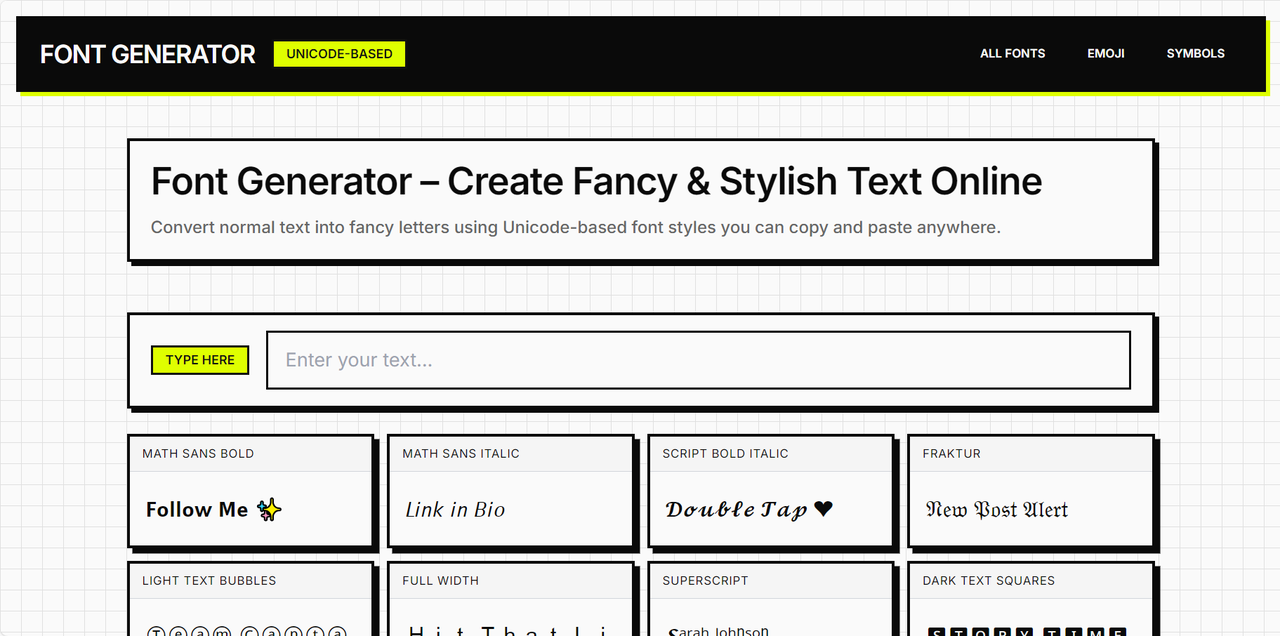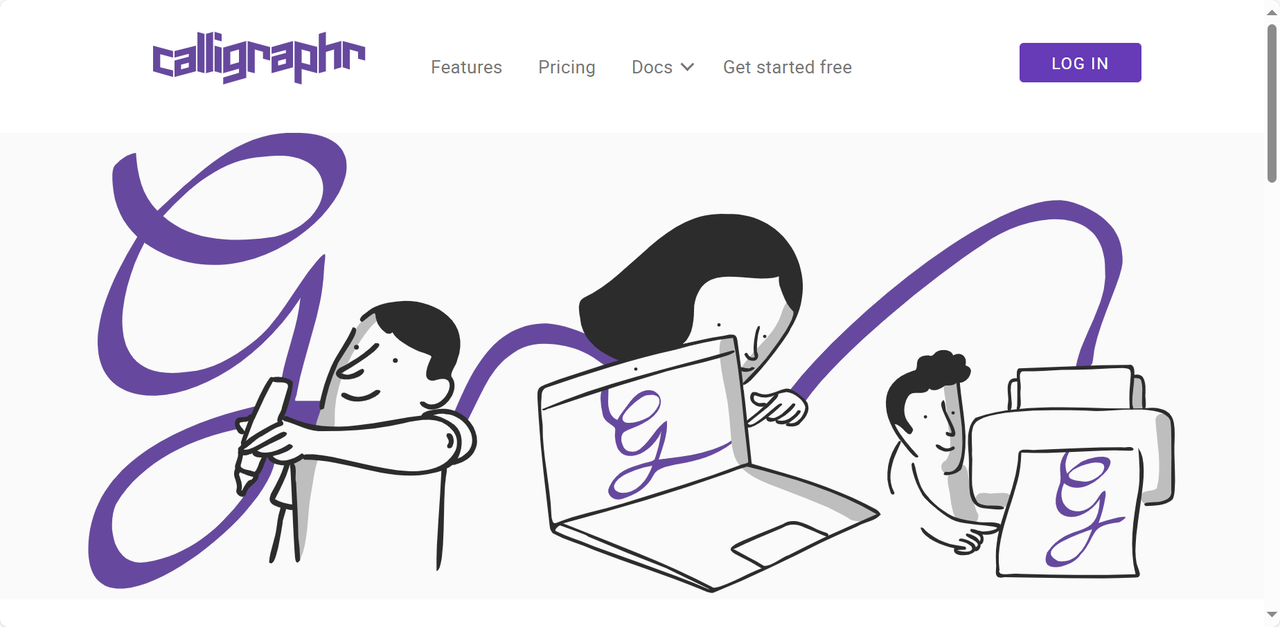
不用安装软件!在线实现字体转换,多重风格任你挑
经常做设计的小伙伴们都知道字体的重要性,往往系统自带的字体库是不够用的,普通字体也难以达到我们想要的效果,全网搜刮字体还总会遇到各种广告。今天给大家整理了 6 款不用安装软件就能使用的字体转换器,打开网页就能用,多重风格任你挑选。即使是新手小白也能快速进行字体转换,得到自己满意的字体效果!这些字体转换器的操作逻辑各不相同,擅长的字体风格也不太一样,接下来会给大家详细介绍每个工具的特色功能,帮助你选择最适合的自己的那一款。
一、字由
字由是一个集字体资源、字体管理和 AI 工具于一体的综合性工具,目前注册用户远超 2000 万,累计收录了上万款字体资源,明确标注可以免费商用的字体也有 3580+ 款,几乎适配所有日常需求。
关于字体转化,字由也为大家提供了多种方式:
- 第一种:实现多种风格的字体转化
进入字由官网之后,点击【全部字体】,这里有超多不同类型的字体资源,按照风格或字体类型可以进行筛选。选中你心仪的字体,在字体详情页面输出文字,就能一键转化为当前的字体效果,非常方便。最值得一提的就是,这些字体资源都清晰标注了授权类型,保证让大家放心使用,免遭版权问题的困扰。
- 第二种:实现艺术字的转化
同样也是进入字由官网,在顶部导航栏找到【字体工具】-【 AI 字体】,这也是字由的特色功能之一。这里有丰富多彩的艺术字模板,比如霓虹效果、书法水墨风、涂鸦风、文艺手写风等等,每一款都能让你的作品瞬间出彩!用户只需要选择自己喜欢的模板,点击“做同款”,在文字区域输入自己想要的文字内容,点击“立即生成”,等待几秒钟就可以获得同款字体,完成艺术字的转化。字由支持将字体下载为透明背景的 PNG 格式,后续直接拖进其他设计软件中就能用。
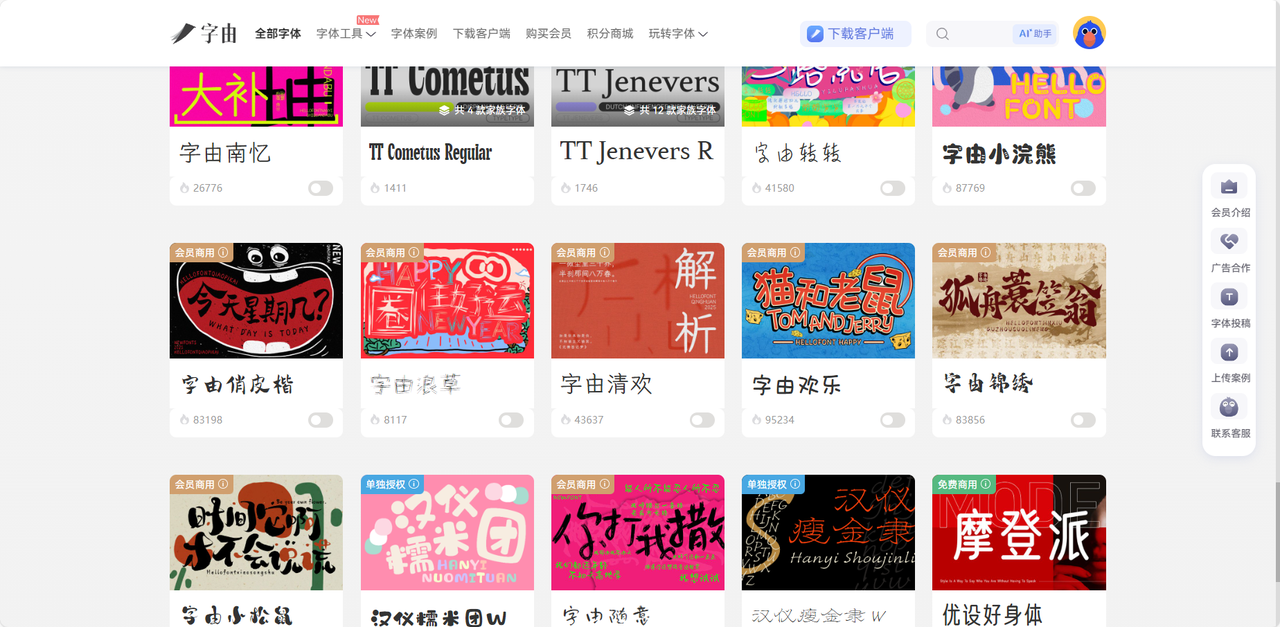
二、FontGenerator.design
FontGenerator.design 可以快速完成字体风格的转化,打开网页输入文字,你就能看到上百种不同风格的文字效果,并且可以将文字一键复制粘贴到任何支持 Unicode 的地方。这款字体转化器免费且没有转化次数限制,界面设计简单,新手设计师也能快速上手使用。它最大的亮点就是专门按照使用场景进行了字体的划分,比如适合放在 Instagram、Twitter、Roblox 等不同平台的字体,这里都进行了汇总整理,并且每个分区都提供了最受欢迎的字体样式便于大家选择。需要注意的是,FontGenerator.design 转换的文字不是独立的字体文件,在不同设备或者是不同操作系统上可能会显示异常。喜欢频繁更换社交媒体个人资料、喜欢花里胡哨的文字介绍的小伙伴,用 FontGenerator.design 是个不错的选择!
三、Calligraphr
Calligraphr 是一款可以让手写笔迹转化为电脑上安装使用的字体文件的工具,真正做到了字体的独一无二。和以上的字体转化流程不同,用户需要登录 Calligraph 官网下载对应的 PDF 模板并打印出来,在对应区域用黑色签字笔逐一填写字母、数字或符号,然后拍照上传,该工具系统会自动检测你的手写轨迹,从而生成字体文件。Calligraphr 生成的字体可以直接安装到电脑系统,后续在任何设计软件中都可以直接应用哦,这就是带有你自己的书写温度的字体。Calligraphr 最大的特色功能就是字符随机化。它可以为同一个字符设置十余种不同的变体,系统在生成字体文件的时候会随机排版,从而模拟出真实手写的差异,让字体看上去像是自己一笔一画写出来的那样逼真,效果非常好,大家可以去试试哦。
四、FontStruct
FontStruct 是一个可以自己建造字体的字体转化器,也就是说,用户可以通过搭积木的方式拼出你喜欢的字体。只需要打开 FontStruct 的网页,在网格画布上放置或者移除不同类型的积木,比如三角形、方形、圆形等几何形状,用你可以将它们组合成各种各样的字体结构,从而创建一套新的字体。我觉得这个字体转化器还是比较考验用户的空间感和审美观的,毕竟是需要从零搭建一个字符,追求省事的小伙伴可以尝试别的工具哈。如果你喜欢像素风或者科幻风,FontStruct 的确是个最佳选择,用它制作出来的字体很适合用于像素游戏、科幻未来感场景、几何极简风场景等,是一个非常有创造力和艺术感的工具。
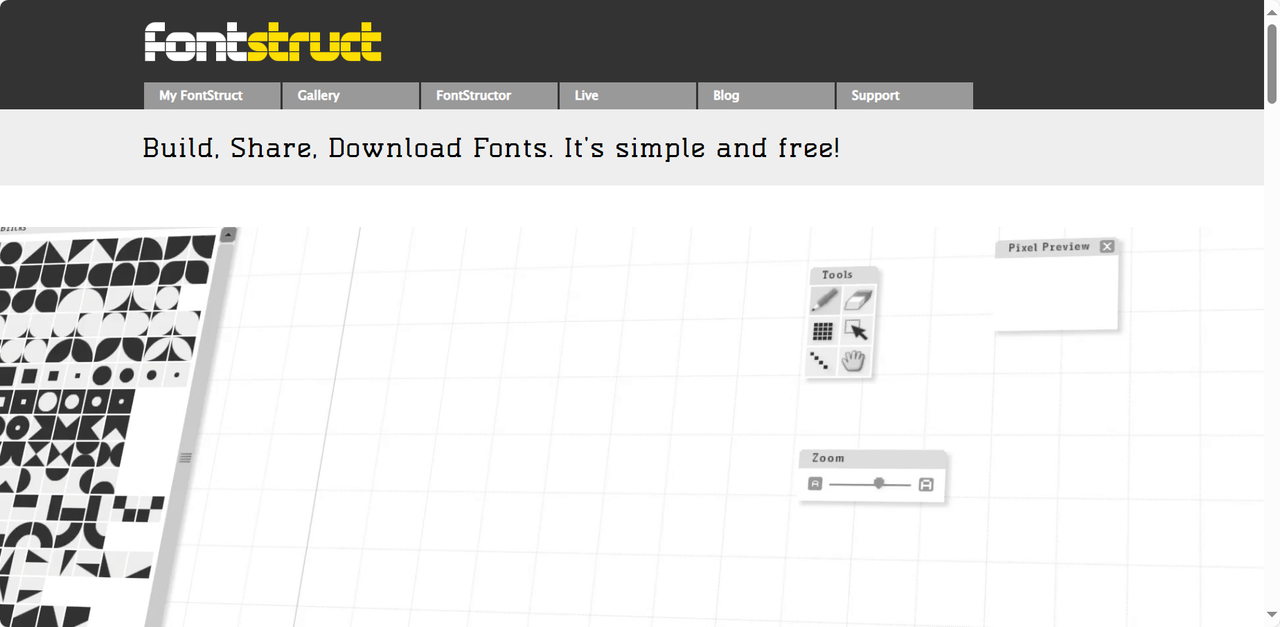
五、mloudConvert
和上述的字体转化器不同,CloudConvert 不是转化字体风格,而是转化字体格式,是一款功能极为全面的云端字体文件转化平台。它支持 TTF、OTF、WOFF、WOFF2、EOT 等主流字体格式之间的相互转换,无需安装任何软件,打开网页即可操作。最重要的是,CloudConvert 的操作流程非常简洁,仅需三个步骤:拖拽字体文件、选择转化格式、点击转换。对于想要一次性转化多个字体文件的用户来说,CloudConvert 也完全没问题,它支持在线免费批量转换,大大提升了大型设计团队的工作效率。
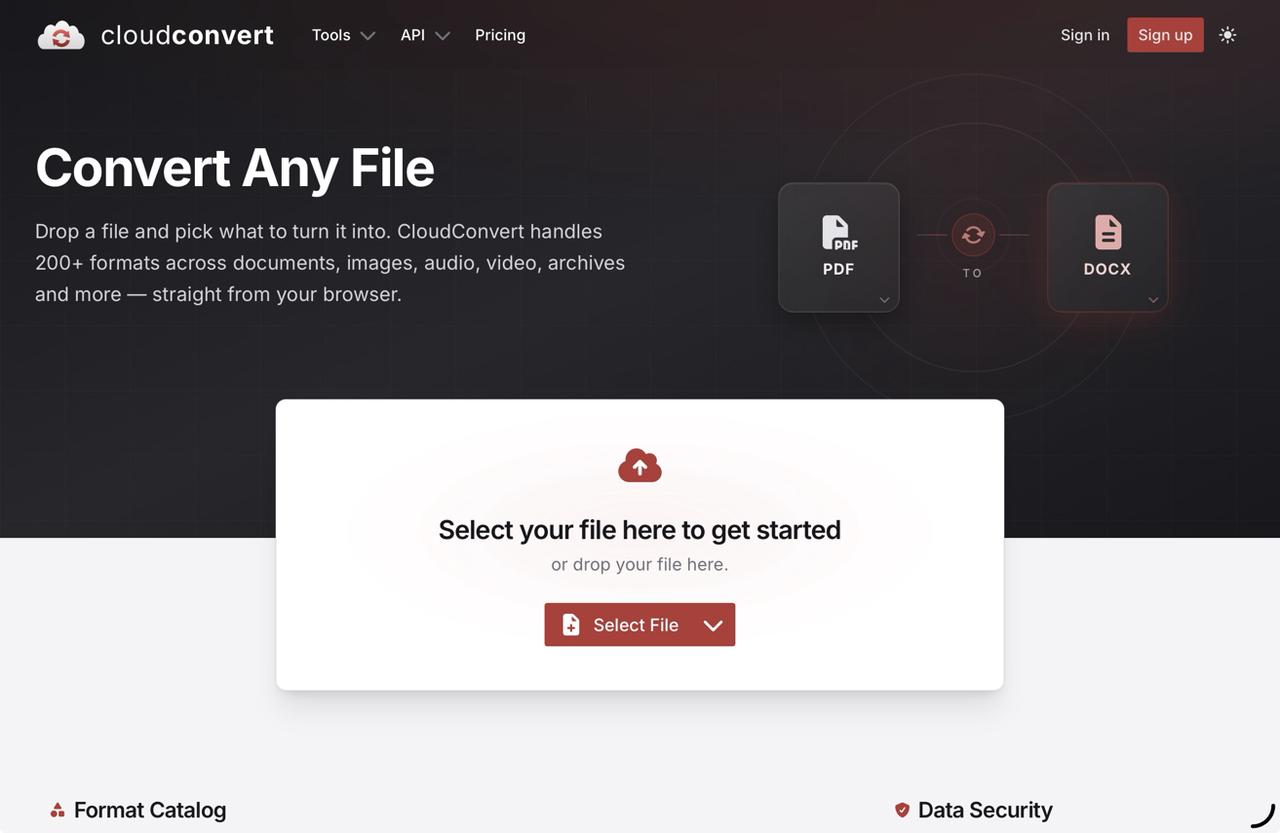
六、FontForge
FontForge 是一款历史悠久的开源字体编辑工具,在字体转化方面也非常出名,它不仅能创建编辑多种不同类型的字体文件,还可以转换出各种格式的字体。在 FontForge 上,用户有充分的自由度,你可以自己绘制字形轮廓并调整字体间距,想要什么样的字体都可以随心而定,不过这也需要你有一定的设计能力,新手小白不建议尝试。FontForge 最大的优势功能就是脚本自动化,会编程的小伙伴就可以编辑自动化脚本来批量转化字体,普通用户也可以用它转化字体格式,常用的字体文件格式都可以转化成功哦。